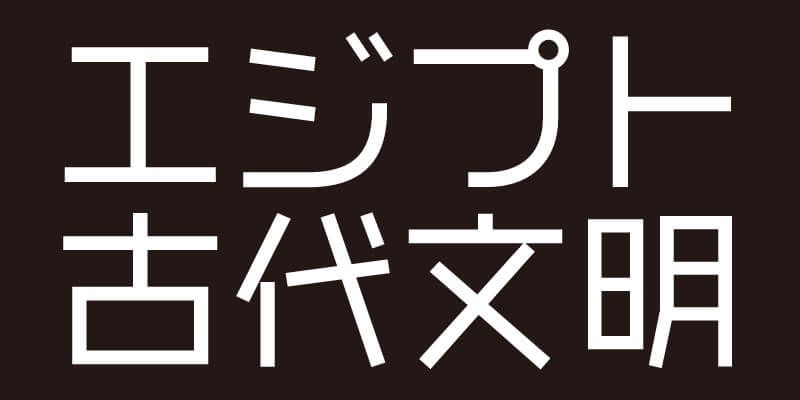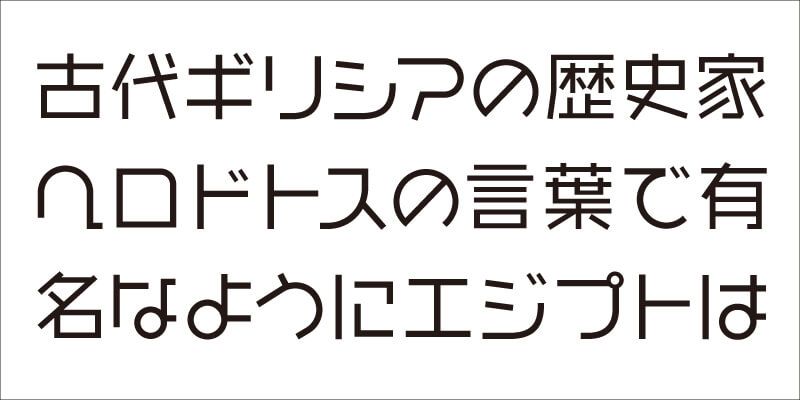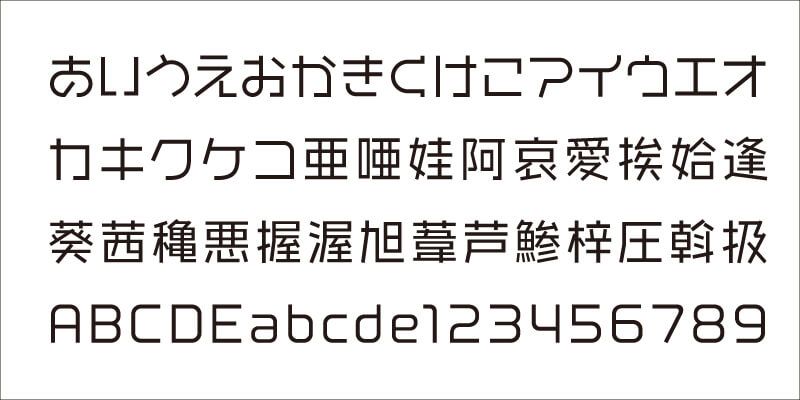
VDL-GigaJr è una variante “junior” di VDL-GigaG, disegnata con linee semplici e rette, come se fosse composta da frammenti di nastro di carta. Il tema centrale di questo progetto di design dei caratteri è “Divertiti e sii libero!” I caratteri sillabici kana e i glifi alfanumerici sono stati progettati di recente con linee rette e archi per armonizzarsi con il design chiaro dei suoi caratteri ideografici. VDL-GigaJr stimolerà i sensi dei professionisti creativi e li aiuterà a produrre espressioni grafiche efficaci.
L’ethos di Visual Design Laboratory (VDL) è quello di bilanciare la bellezza naturale delle lettere con standard rigorosi di leggibilità. VDL offre una raccolta completa nota come “VDL Designers Fonts” (VDLデザイナーズフォント), che trova sicuramente il favore dei progettatori alla ricerca di un carattere altamente individuale che mantiene al tempo stesso un ampio fascino.